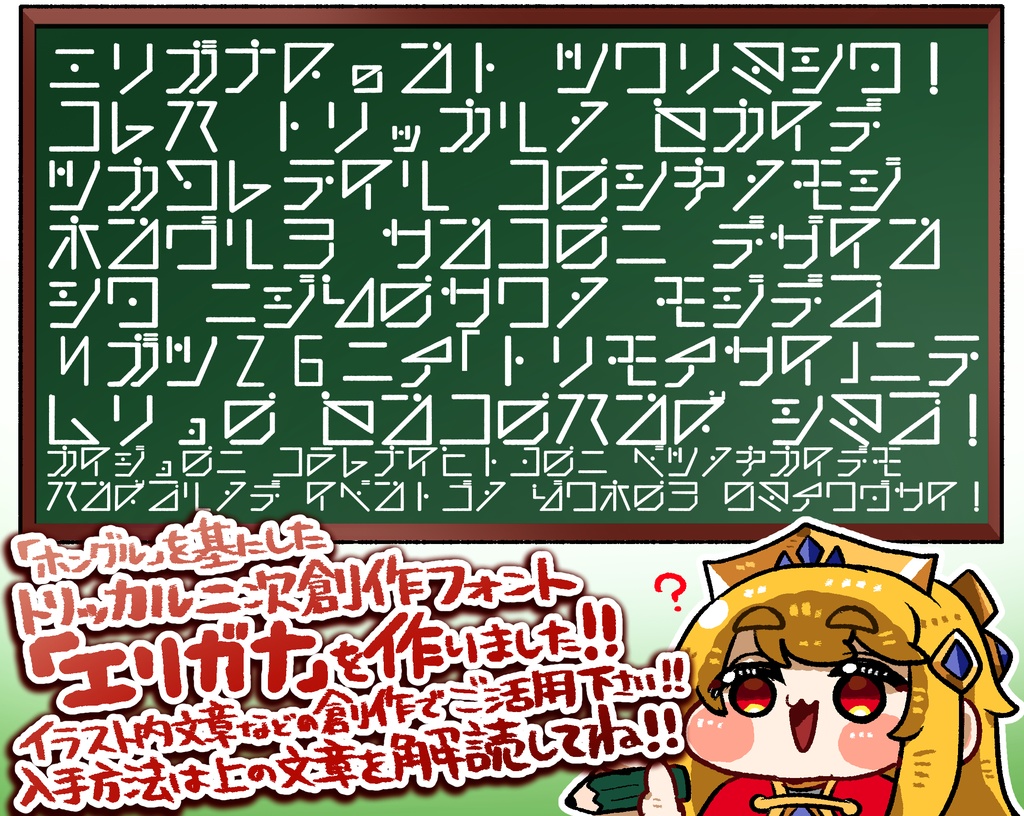
ばーちゃるおむち亭エリガナ【トリッカル<二次創作>フォント】Digital0 JPY免费下载Eligana.zip (320.2 KB)Eligana.zipAbout Giftトリッカル公式フォント『ホングル』製作者の「Bttf氏」にご協力いただいて 日本語版ホングル:二次創作フォントの『エリガナ』を作成しました。 世界観になじむ読めそうで読めなさそうな不思議なフォントになっております。 利用規約を一読し、ぜひトリッカルの創作活動にご利用ください! ◆ghost、fairy、animal、sugar、witch、master、elf、dragon、mystic、spiritを英語で入力すると、自動的に特殊文字に変換されます。ばーちゃるおむち亭Visit FANBOX!Comic Market 108Illustration & CG collectionsエルフィン、美術館に行く。<オムチソバイラスト集>/DL版【C108】ばーちゃるおむち亭400 JPYComic Market 108Keychains & Charms & StrapsOut of Stockお座りキーホルダー<ネル>【C108】ばーちゃるおむち亭1,700 JPYComic Market 108Acrylic KeychainsOut of Stock水着ポーシャーアクリルキーホルダー【C108】ばーちゃるおむち亭2,200 JPYBody-pillow CoversOut of Stockエルフィン抱き枕【C108】ばーちゃるおむち亭11,111 JPYMangaエルフィンのおこづかい/DL版【第1回トリもち祭】ばーちゃるおむち亭450 JPYAcrylic Figure正面スピキアクリルスタンドフィギュア【第1回トリもち祭】ばーちゃるおむち亭1,700 JPYAcrylic Keychainsエルフィンぷらりこアクリルキーホルダー【第1回トリもち祭】ばーちゃるおむち亭1,200 JPY查看更多